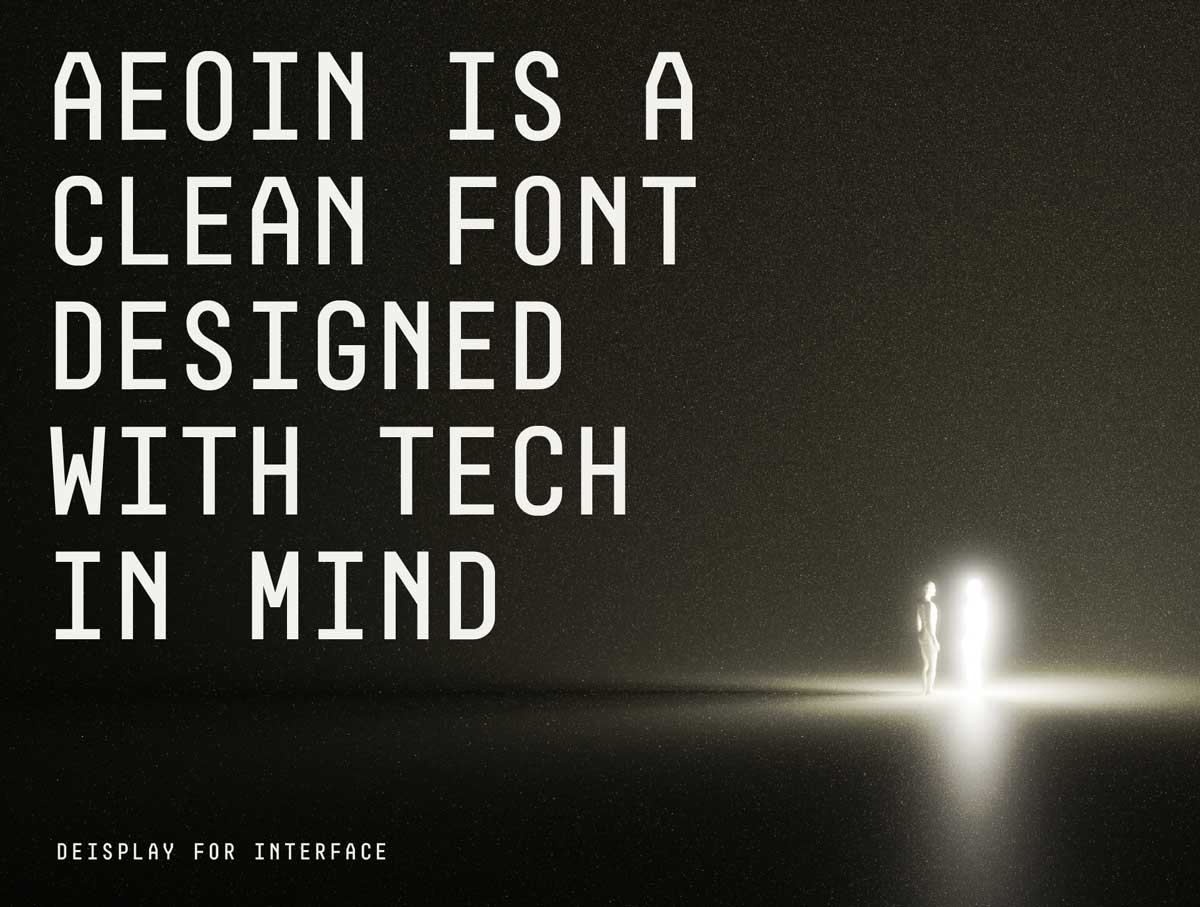
Aeion英文字体设计素材.otf .ttf .woff安装包(Aeion Mono Spaced Variable Font Family),Aeion Font 是一种压缩的单倍行距字体,有 7 种粗细和一种可变字体。它的设计考虑到了技术。这种字体散发出严肃的能量,就像,很难用 Aeion 输入一个笑话。它是现代的,带有一点复古的氛围,非常适合任何现代项目。如果您喜欢科技,Aeion 非常适合作为海报、品牌、社交媒体、杂志、徽标或其他任何的显示字体。